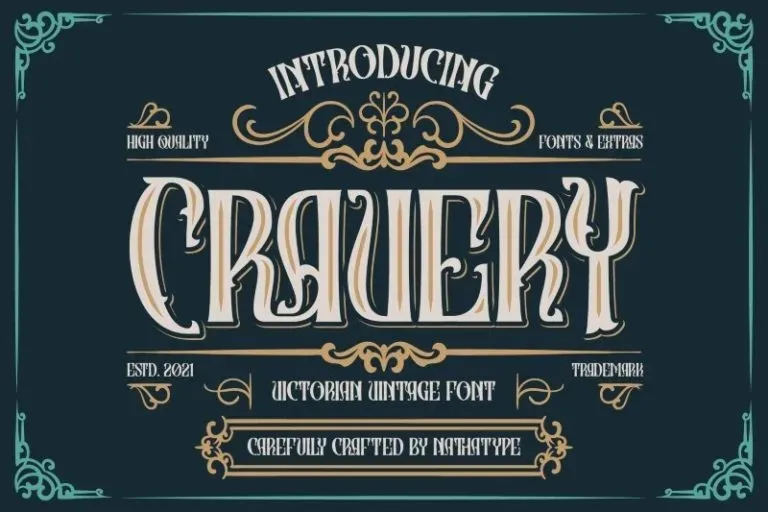
Cravery Font – Fonte Grátis
Cravery Font
A Cravery Font é uma escolha excepcional para aqueles que buscam incorporar toques vintage ao design moderno, com um estilo elegante e artístico inspirado no Victoriano. Criada pela Din Studio, essa fonte blackletter traz uma essência única e antiga que certamente enriquecerá projetos variados como logotipos, capas de livros, cartazes, camisetas, marcações e anúncios. Seu aspecto artístico é versátil o suficiente para se adaptar a diversos tipos de projetos, tornando-a uma opção perfeita para todos aqueles que desejam um ar retrô envolvente em seus trabalhos. Com sua elegância vintage e estilo único, a Cravery Font certamente não decepcionará quem valoriza o equilíbrio entre o tradicional e moderno em seu trabalho de design.